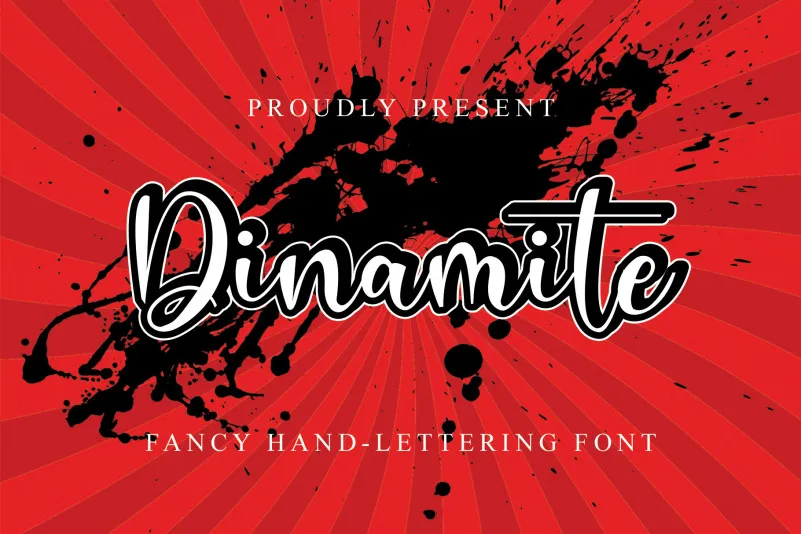
Dinamite Font é uma fonte escrita a mão que cativa os amantes do estilo descontraído e único. Inspirada na ideia de ser ‘fun’, este tipo parece deslizar facilmente sobre diversos ambientes, desde cartazes comerciais até pequenos recortes em jornais. Uma corriqueira dose de irreverência enriquece sua personalidade, tornando-a uma escolha versátil para qualquer contexto visual. Inspirada por um designer talentoso da Erik Studio, a Dinamite Font traz diversão e criatividade ao seu design digital. Seja você um criador de conteúdo, um profissional de marketing ou apenas alguém que quer adicionar um toque único às suas mensagens digitais, esta fonte certamente fará sua marca.